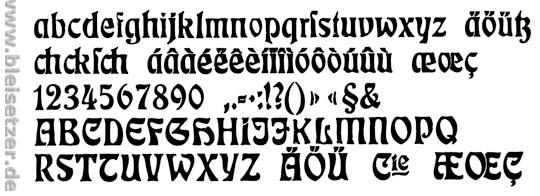
Suche Schrift (Geht leider nicht aussagekräftiger)
Hallo, ich suche die Schrift zum unten angegebenem Beispiel.
Kennt sich jemand mit Jugendstilschriften aus?
Naja, das Beispiel zeigt ja keine Jugendstil-Schrift,
sondern eine Schrift mit ein paar Kringeln dran.
Eine Jugendstil-Schrift ist so was:
(Was Du natürlich selbst weißt, aber ich wollte die Eckmann so gern mal wieder hier hochladen)
Die ist ja auch schön, muss man von Zeit zu Zeit mal sehen ... und richtig, ich bin wegen der "hochgezogenen" Diagonale beim N drauf reingefallen, ist aber wohl eher sowas 60er/70er-artiges ...
in den 60ern gezeichnet und soll an die 20er erinnern, joh.
ich mag den font.